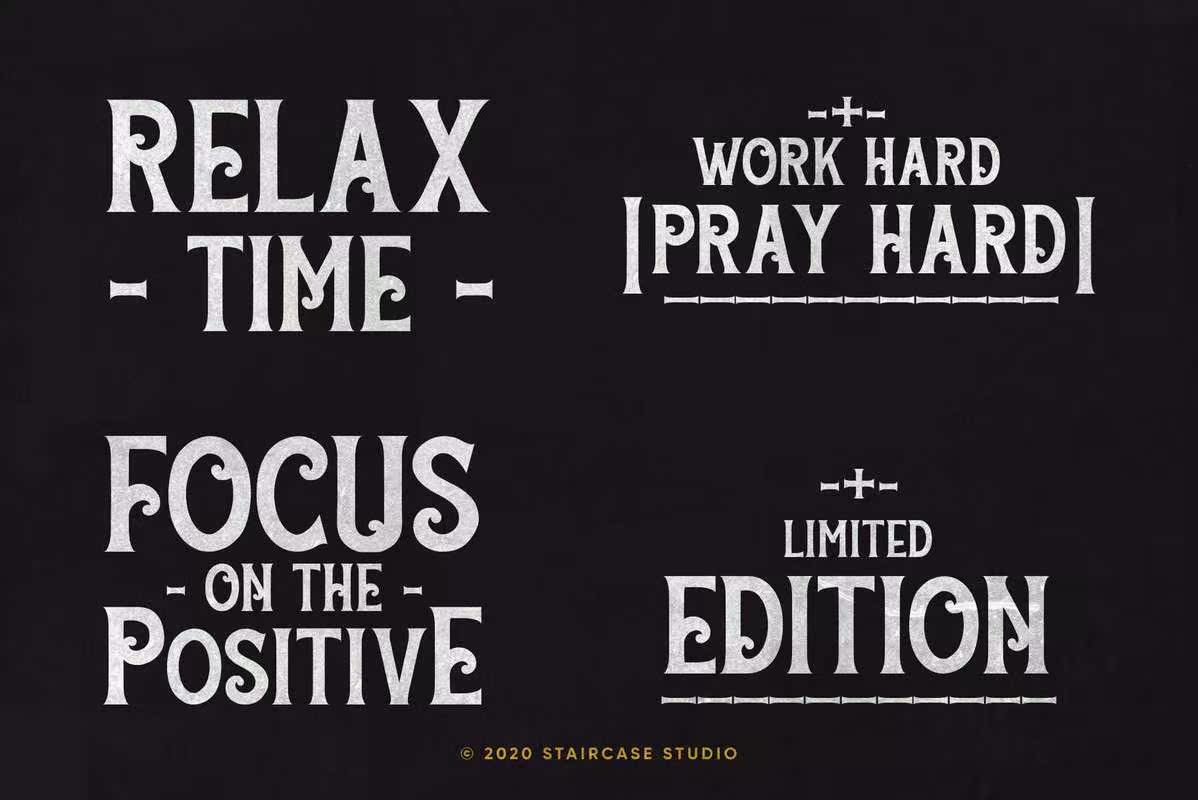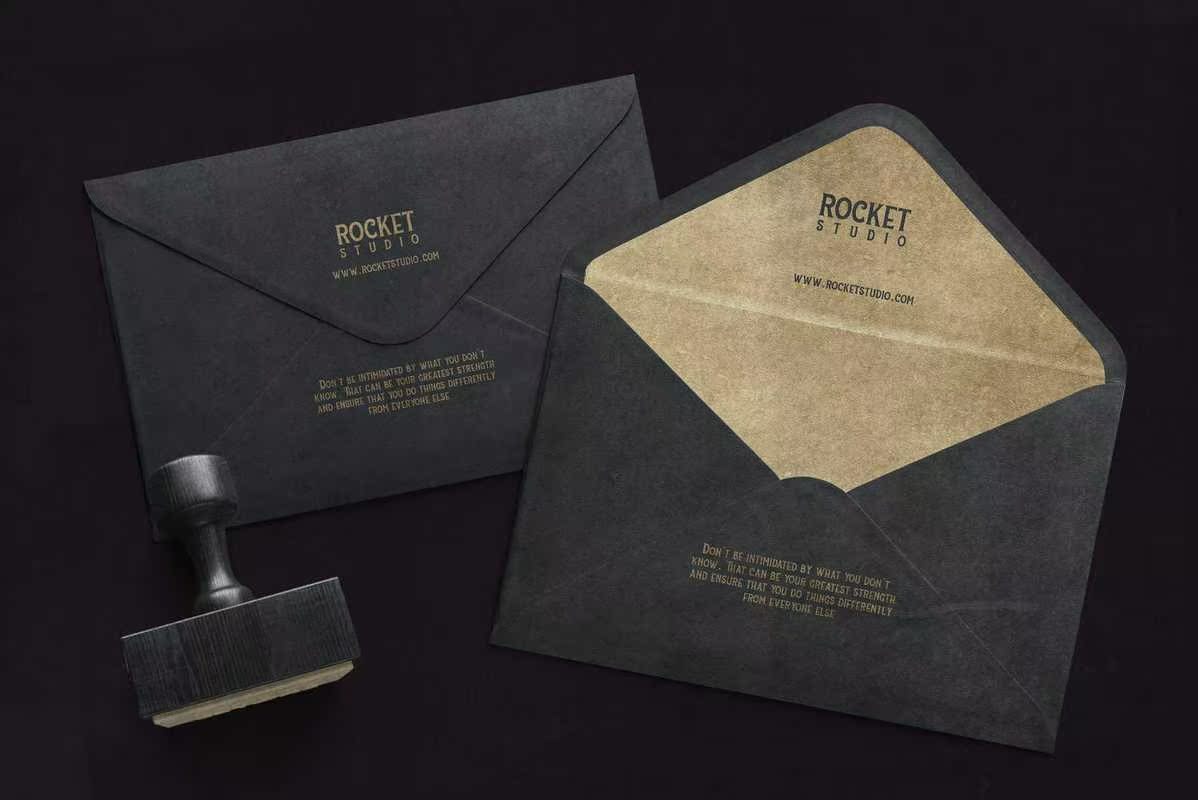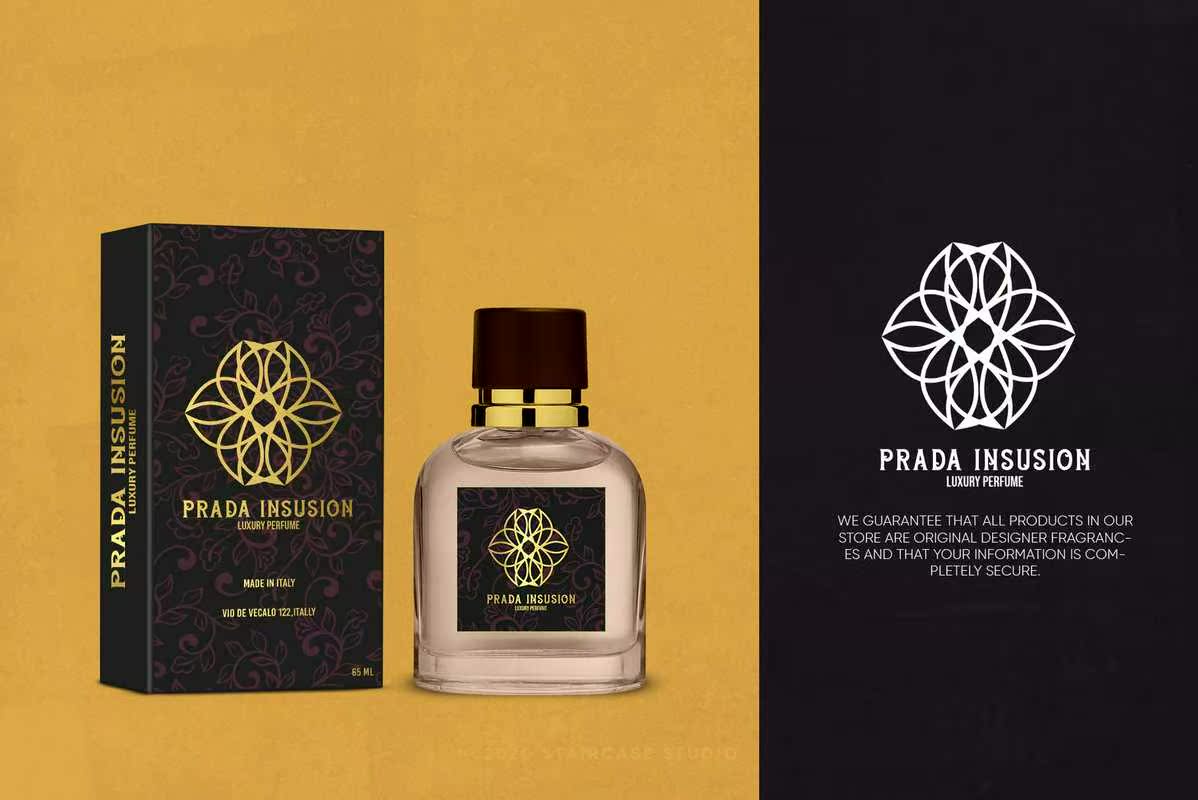
具有全新和现代风格的RocketVintageFont。适合您的项目的文字和数字集合非常适合于标识、品牌设计、标识设计、数字刻字艺术、T恤/服装、海报、杂志、标志、广告设计和任何设计需求。具有全新和现代风格的RocketVintageFont。适合您的项目的文字和数字集合非常适合于标识,品牌设计、标志设计、数字文字艺术、T恤/服装、海报、杂志、标志、广告设计和任何设计需求。